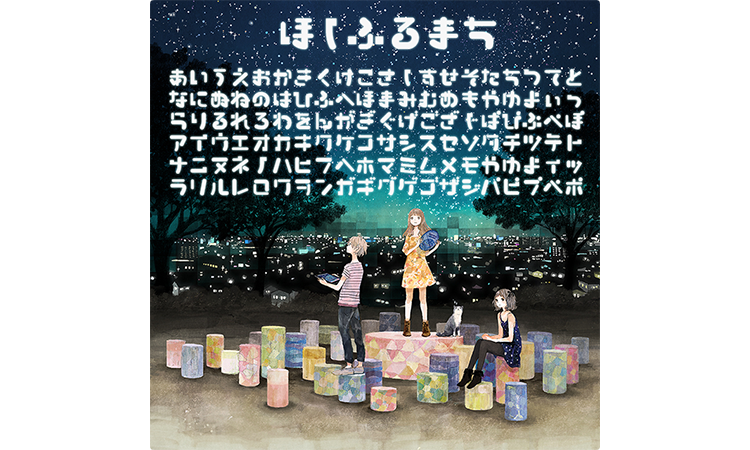
ほしふるまち
ほしふるまちは、空から見下ろした道をイメージして作成されたユニークなフォントです。本来の書き順を無視して作成されており、それがユニークで印象的なデザインを生み出しています。見出しやロゴなど大きなサイズでの使用に向いています。
基本的にひらがなとカタカナのみのフォントです。漢字はごく一部が収録されています。足りない漢字は丸ゴシック体のフォントと組み合わせて使います。例えば、モリサワじゅん、ダイナフォント太丸ゴシック体などと相性がいいです。
ほしふるまちのサンプル